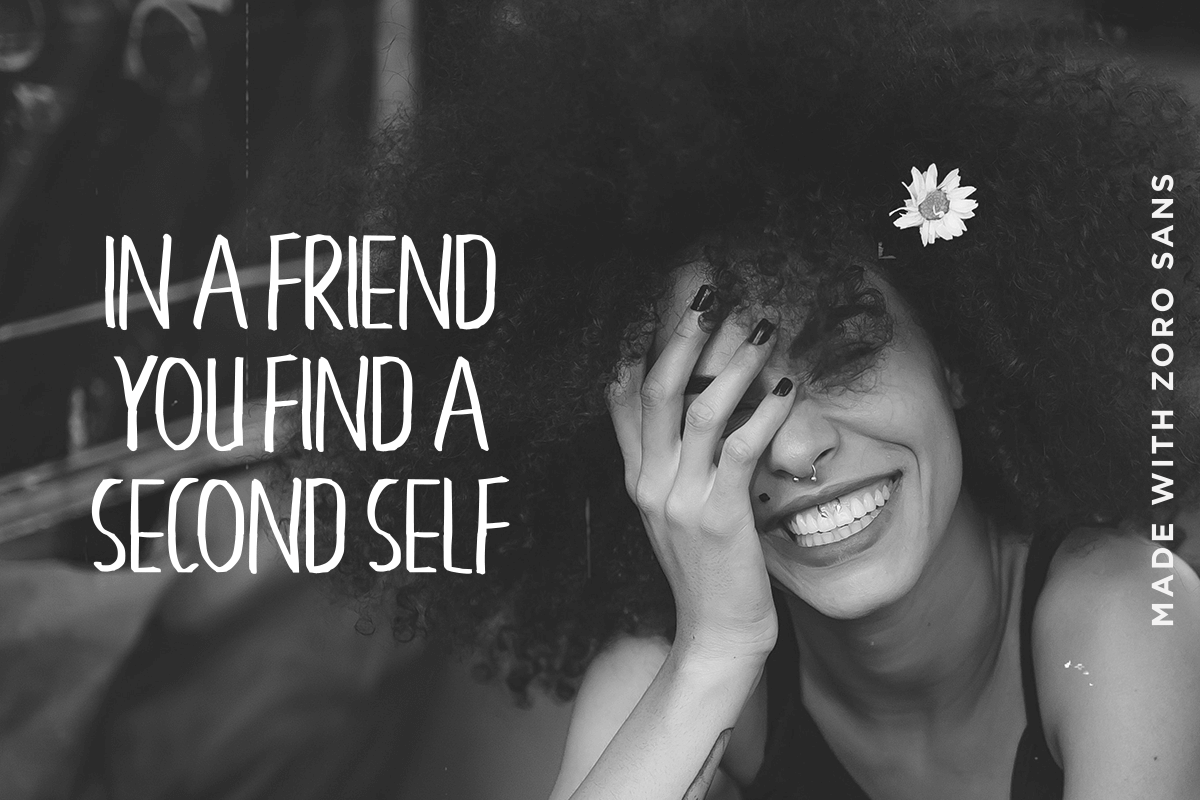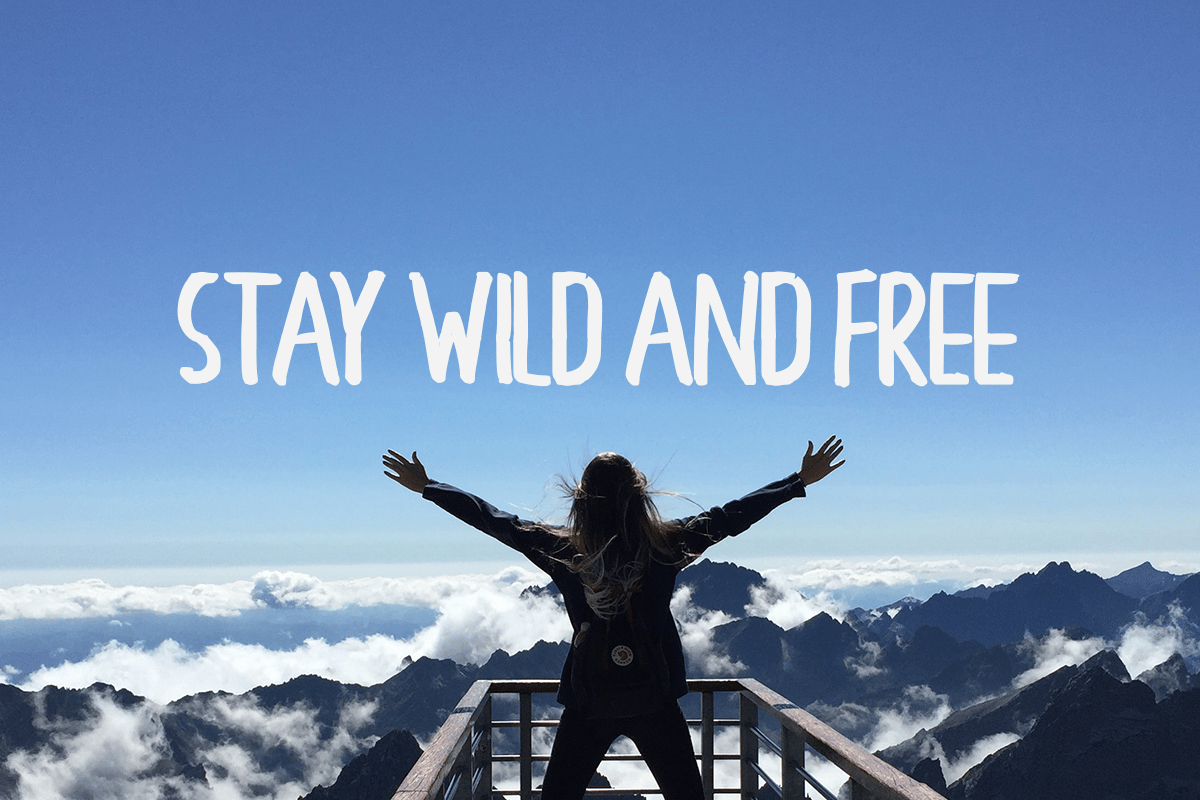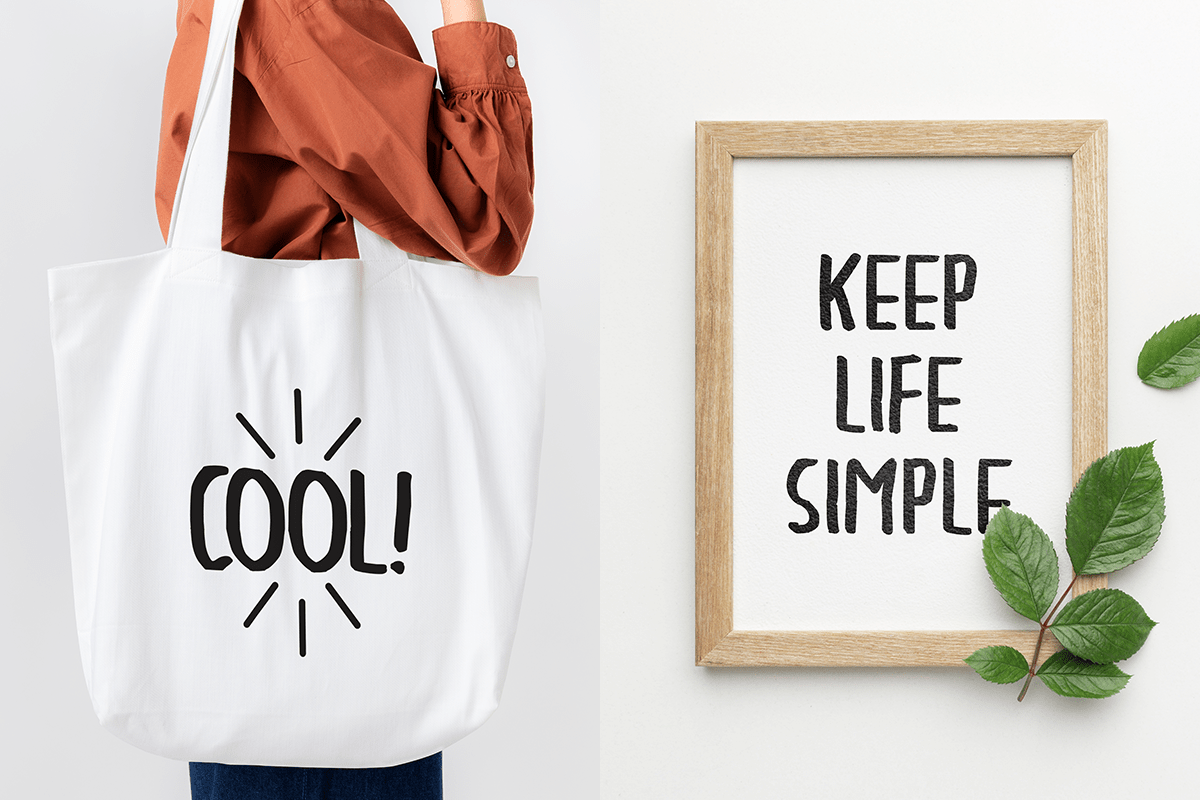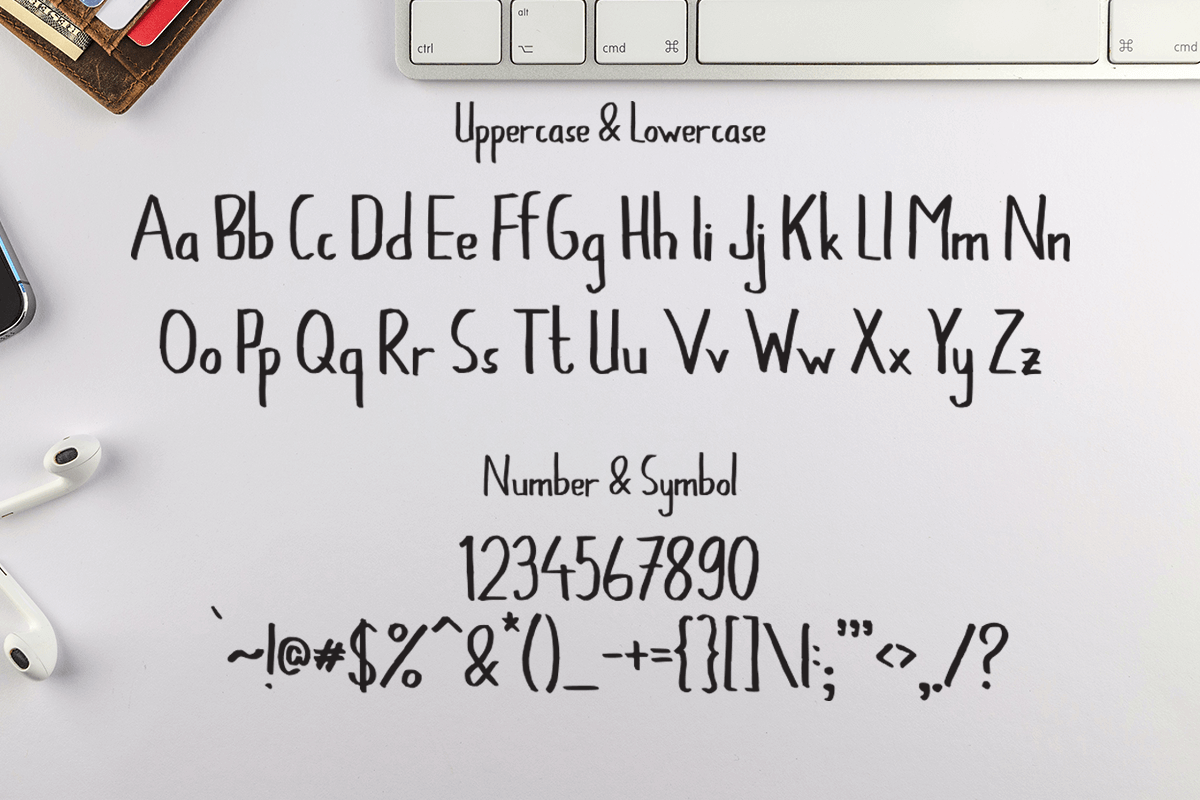
Zoro 字体下载,这款字体结构工整、笔画清晰,兼顾美观与易读性,适用于标题、正文、海报、包装、LOGO 等多种场景。字形优雅稳定,风格百搭耐看,适配日常排版与创意设计,让文字呈现更舒适、更具质感。Zoro 字体下载一笔一画,皆是细节,以均衡的比例、流畅的线条打造舒适视觉体验,字形端正大气,风格简约现代。无论是商业设计、品牌宣传还是日常排版,都能轻松驾驭,让文字更有格调与力量。Zoro 字体下载字体下载。
Zoro Display 字体介绍
This font is a handdrawn font. It has an authentic texture – giving it a look as if it just left your pen. This font is especially perfect for instagram and pinterest quotes.